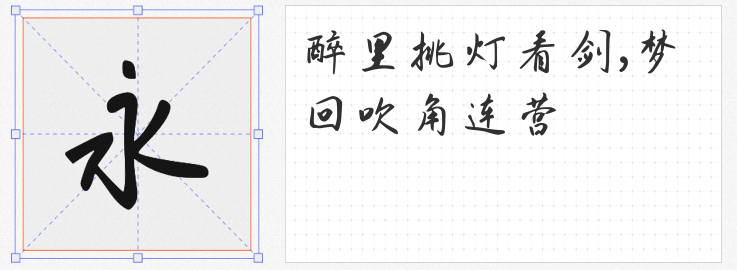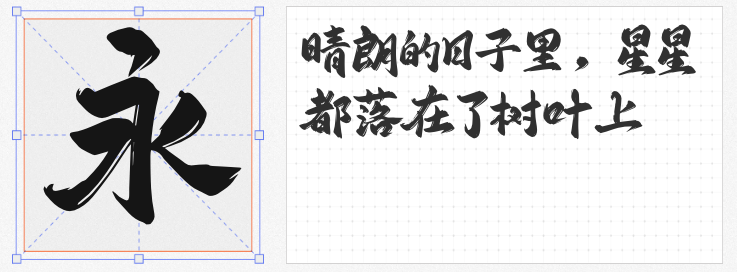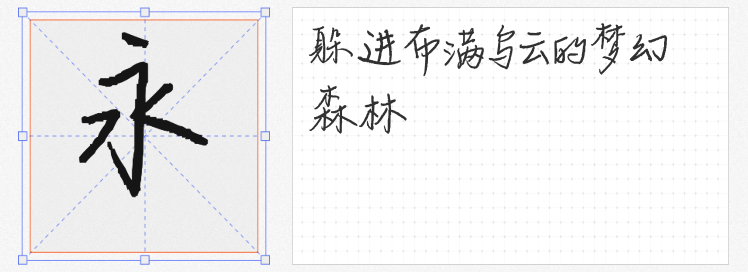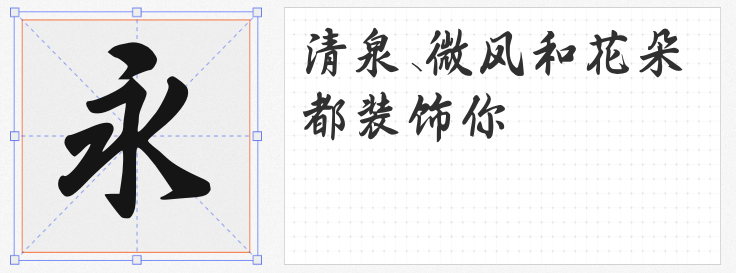
在数字设计领域,手写字体的独特魅力在于其能传递人文温度与情感共鸣。本文精选四款免费可商用的手写字体,涵盖行书、行楷、清新手写及书法风格,满足不同场景的设计需求。
由合肥师范学院毕业、淮北市书法家协会会员熊子杰创作的熊子杰行书,通过AI造字技术将传统书法与现代设计结合。字体以行书为基底,笔画流畅自然,兼具书法韵律感与数字时代的科技感。作为一款免费商用字体,其授权范围明确,适用于广告、标题、品牌视觉等场景。
以母校命名的鼎猎西大体,是一款自由手写行楷字体。其设计理念源于对校园岁月的追忆,笔画不追求完美,反而通过“不完美”传递真实的生活气息。字体包含6769个汉字,覆盖GB2312编码标准,适用于美食餐饮、文化艺术展览、杂志封面等场景。![]()
基于作者手写体制作,包含6763个汉字及数字、标点符号,覆盖日常设计需求。字体笔画简洁明快,结构紧凑,适合VI标准字、企业手册、导视系统等场景。尽管为个人创作,但经过半年校对与测试,确保了阅读的舒适性,是小清新风格设计的理想选择。
由字库星球与甜奈网络联合研发的字库星球飞扬体,融合传统书法美学与现代设计理念。字体笔画灵动富有变化,整体结构流畅自然,传递出飒爽流畅的视觉气场。其应用场景广泛,涵盖标志、书籍、广告、动漫、游戏等领域,尤其适合需要烘托热烈氛围或展现艺术内涵的设计项目。
这四款字体各具特色,从传统书法的韵味到现代设计的灵动,从青春记忆的洒脱到清新风格的治愈,为设计师提供了丰富的创意工具。无论是品牌视觉、文化展览还是日常设计,它们都能以手写温度赋予作品独特灵魂。